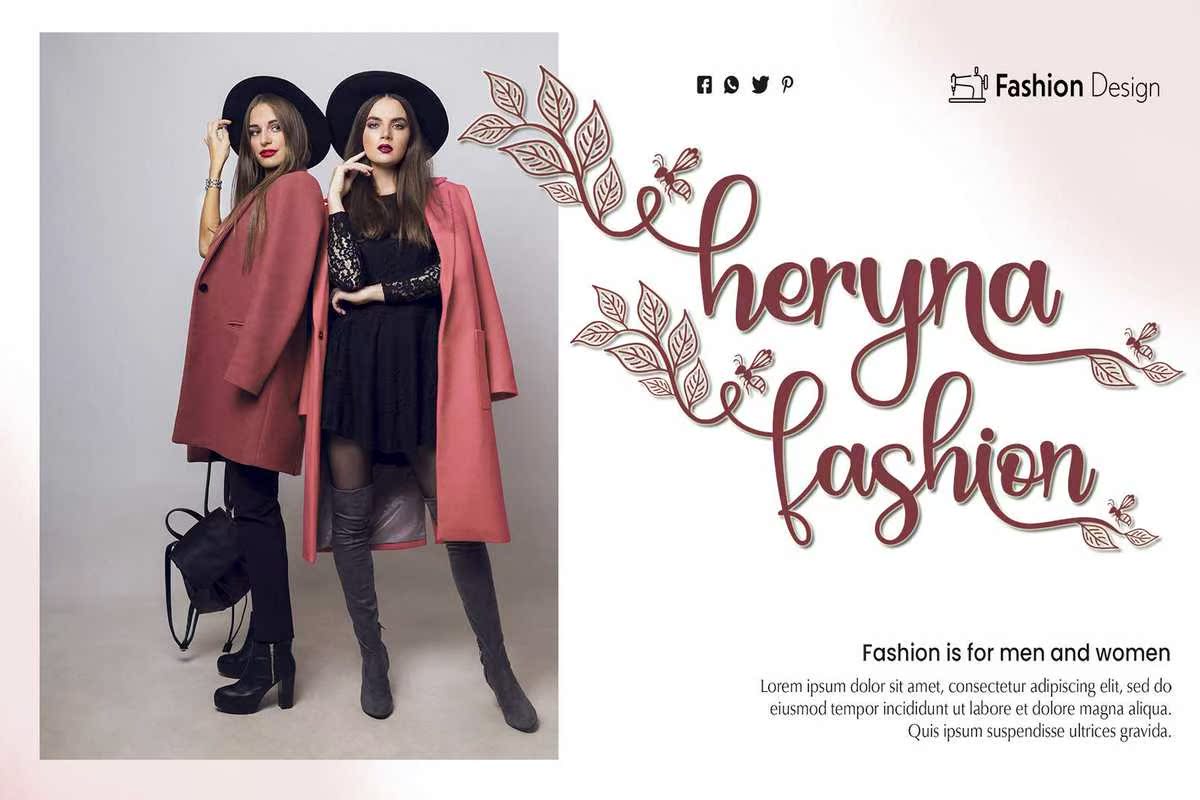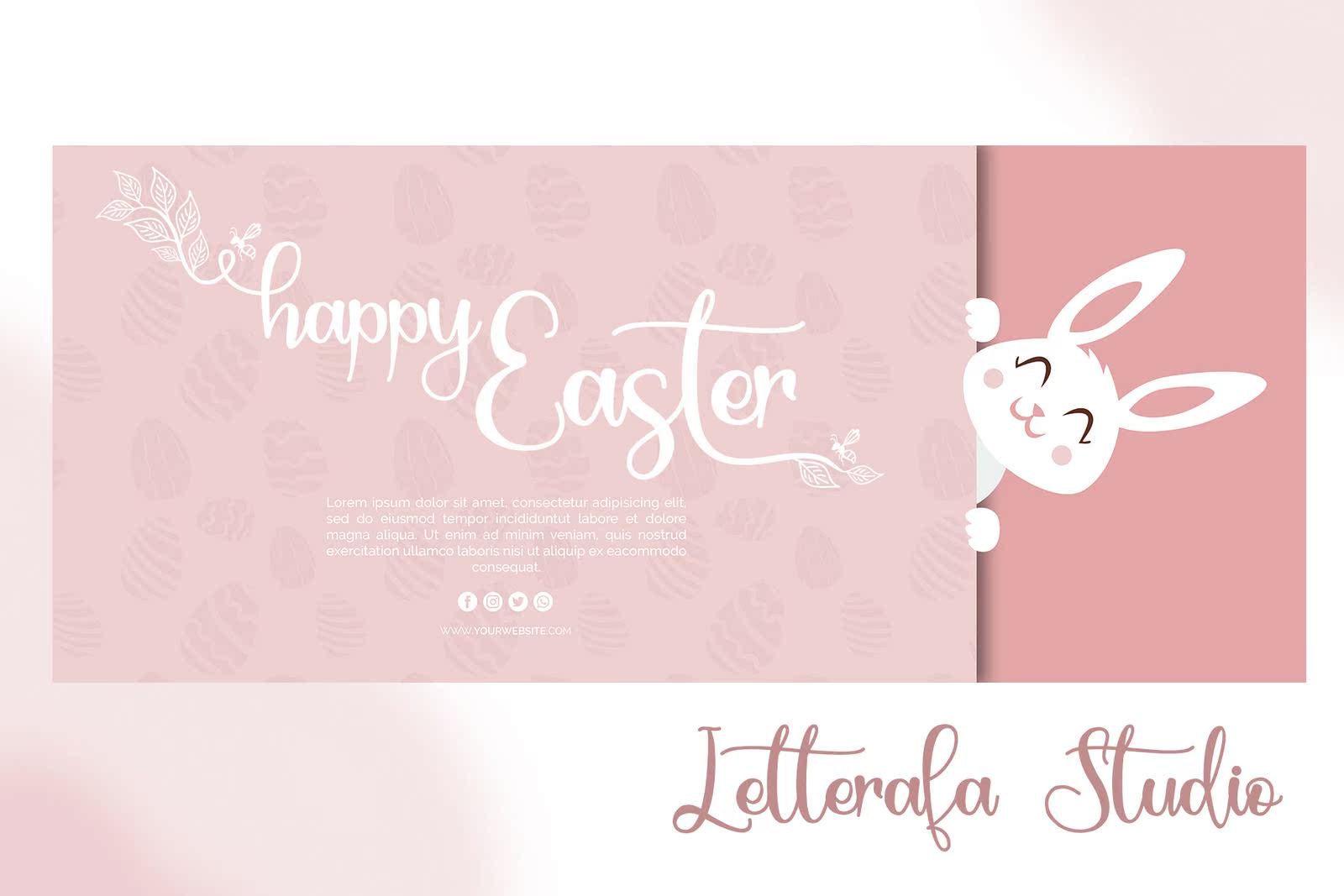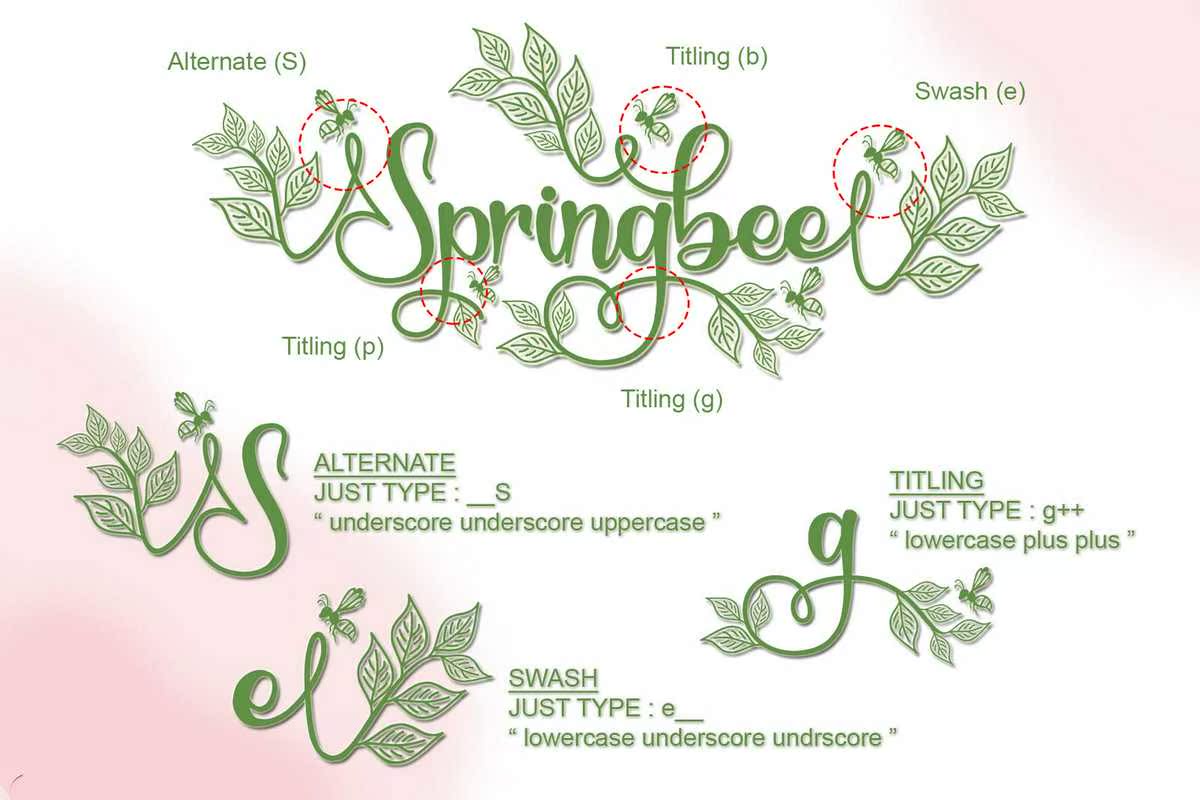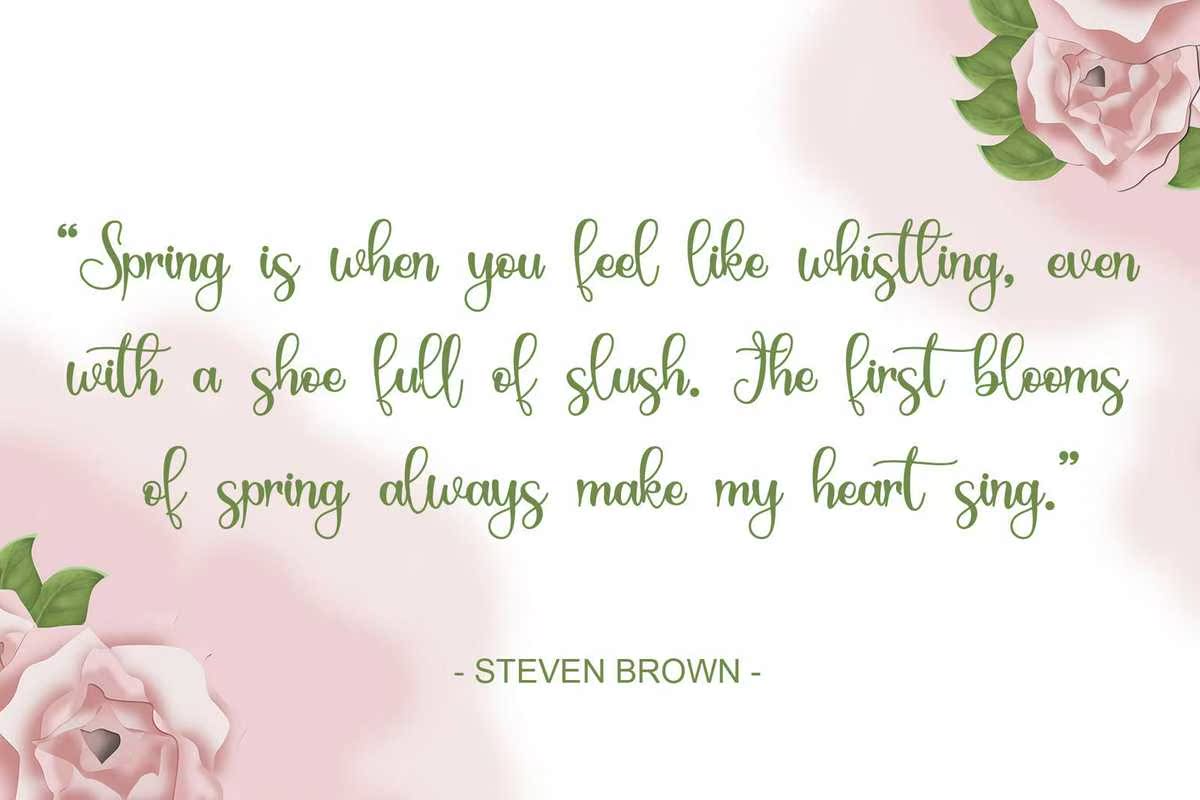
SpringbeeFontIsaModernCaligraphyFontBylettRafaStudio.IthasFlowingLetters将为您的设计注入活力。Springbeefontisperfect;徽标、问候卡、包装设计、耐磨性、工艺设计、任何项目、书名、婚礼宣传、包装等。SpringbeeFont是现代的AlligraphyFontByletterRafaStudio。其流动字母将使您的设计更加完美;徽标、问候卡、包装设计、耐磨性、工艺设计、任何项目、书名、婚礼宣传、包装等。